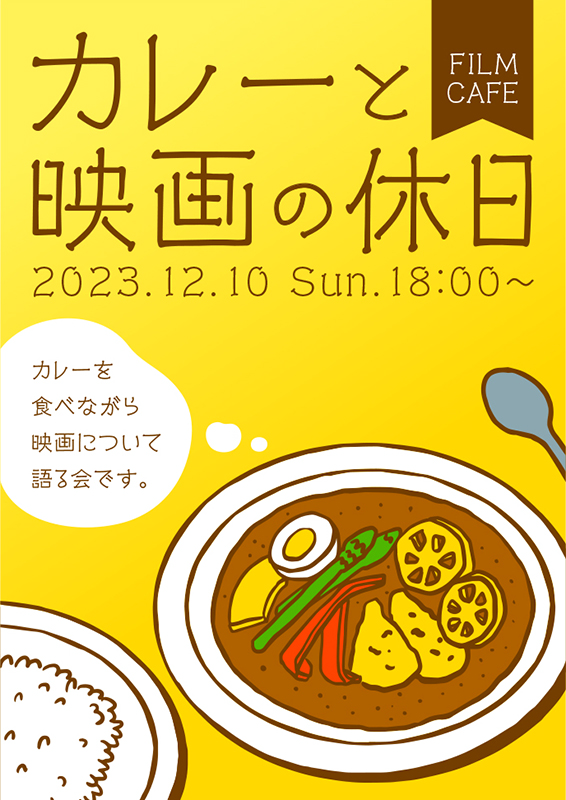
「シネマレター」について
シネマレターは、約30年にわたって映画の字幕を書き続けている職人の文字をもとに作られました。レトロな雰囲気があり、映画関係のチラシやポスターなどのデザインでは特に便利なフォントです。それ以外にも、映画の世界のような雰囲気の演出を狙ったり、あたたかみを強調したかったりするデザインなどで広く活用できます。
「シネマレター」の特徴
シネマレターの文字のデザインは、画線のところどころに隙間が空いていることが大きな特徴です。これは、映画の字幕用にフィルムへと文字を直接刻みつける際に、文字の版とフィルムを剥がしやすくするため、画線に隙間を開けたことに由来しています。
また、スクリーン上で見えやすくするために、映画字幕系の書体は文字の骨格の設計も独特です。シネマレターでは、それぞれの文字の画線の両端に、映画字幕の文字に特徴的な「筆止め」も加えられています。
制作デザイナーの解説コメント
映画にまつわるデザインでまず思い付くフォントですが、そのほかジャンルを問わずに使うこともできる汎用性の高さを備えています。映画にちなんだ演出はもちろん、飲食店のメニューなどに使っても、雰囲気が出て意外にハマりやすいでしょう。